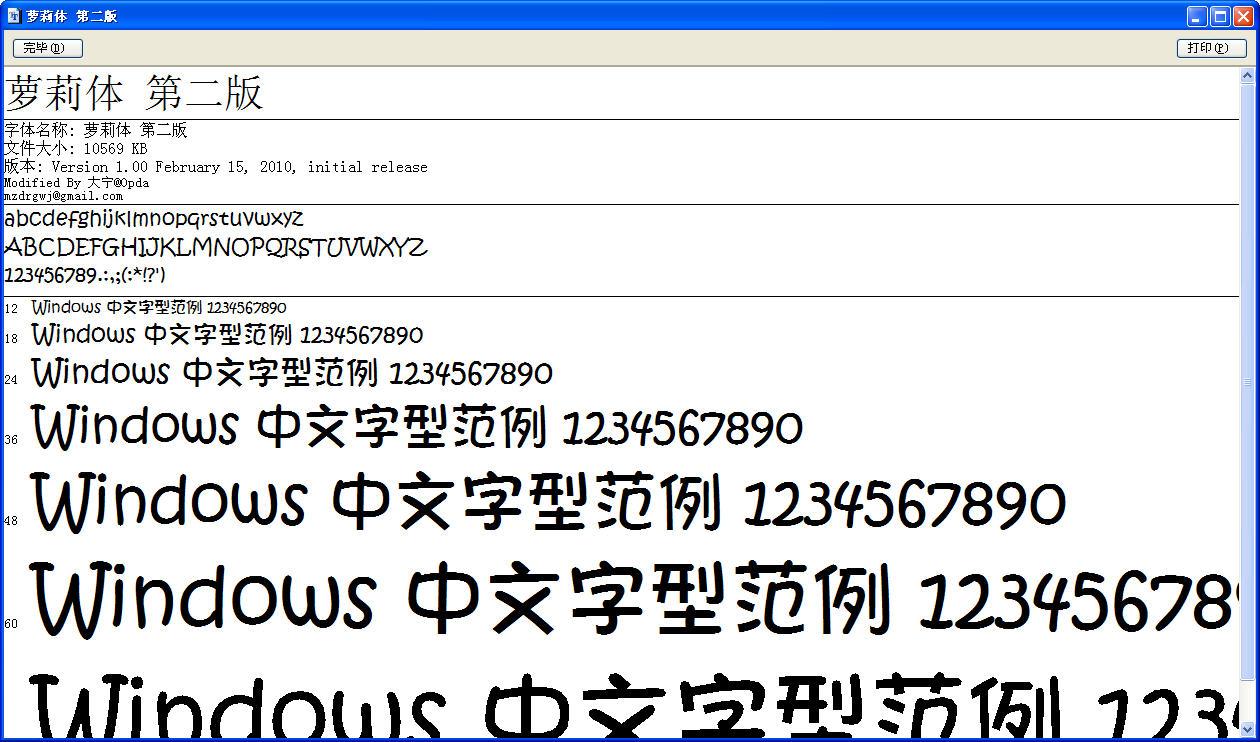
蘿莉字體Lolita V2
蘿莉萌字體第二版是一款看上去非常萌的藝術(shù)字體,這款字體非常適合用來廣告宣傳、藝術(shù)設(shè)計、商業(yè)用字、出版印刷等不同領(lǐng)域,有需要的用戶趕快來本站免費下載使用吧!
字體介紹
蘿莉字體 Lolita V2 第二版 中文字體,看上去有點像娃娃體,不會是娃娃的翻版吧?給需要的朋友,看看下邊的效果圖。
蘿莉字體Lolita V2